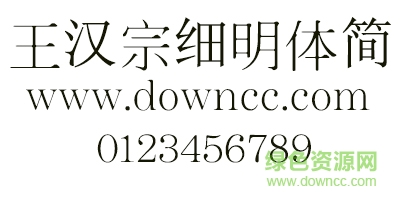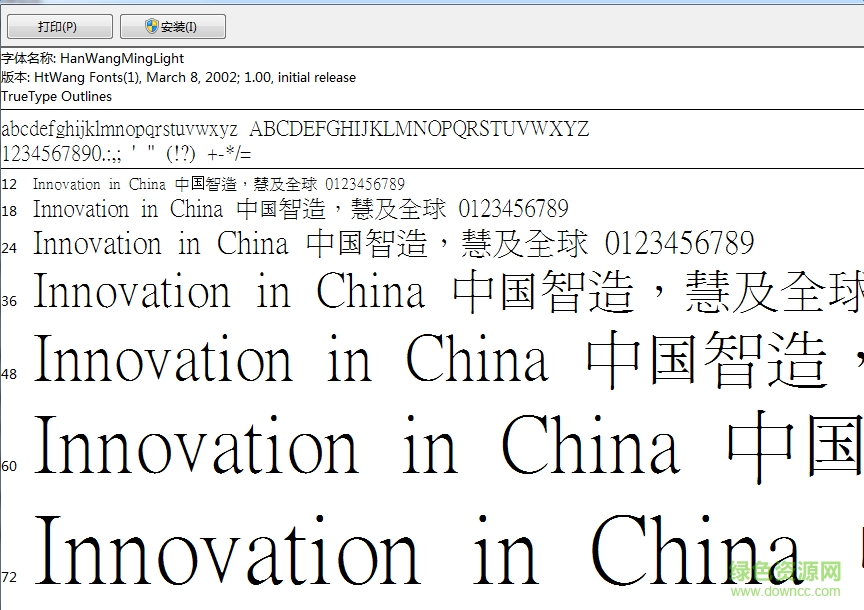
王漢宗細明體包含了簡體和繁體安裝文件。是很受網(wǎng)友們喜愛的一款明體字體。說到他的用途自然是在設計行業(yè)使用的最多了!在制作一些海報、宣傳冊的時候可以使用!歡迎大家來綠色資源網(wǎng)下載安裝。
王漢宗細明體是一款王漢宗字體庫的個性字體,可以廣泛應用于美術設計、新聞媒體、廣告設計、宣傳海報、ppt、影視制作以及內(nèi)容用字等領域,有需要的朋友可以免費下載收藏。
明體是為適應印刷術而出現(xiàn)的一種漢字字體。在中國宋代出現(xiàn)了木版印刷,由于當時的中國書籍每一版印刷兩頁,使用的是長方形木板雕刻制版。木板具有木紋,一般都是橫向,刻制字的橫向線條和木紋一致,比較結(jié)實;但刻制字的豎向線條時和木紋交叉,容易斷裂。因此字體的豎向線條較粗,橫向較細。橫向線條即使比較結(jié)實,在端點也容易磨損,因此端點也較粗。由此產(chǎn)生了豎粗橫細,橫線端點有一粗點的宋體字形。